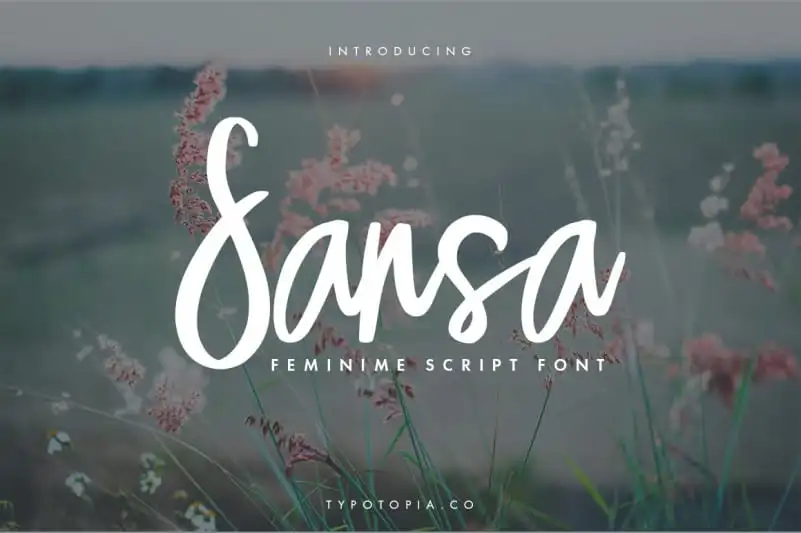
A Sansa Script Font é uma maneira criativa de adicionar personalidade a qualquer projeto que você esteja trabalhando. Ela não é apenas uma nova fonte para escrever letras, mas um instrumento visual único que pode transformar seu design no mais interessante possível. Foi projetada pelo Designer typotopia e é parte da categoria de Fonts Handwritten. Queda dos traços suaves do pincel criam uma aparência original, apropriada tanto para uso personalizado quanto para qualquer projeto. Cada sílaba tem sua própria identidade, promovendo um contato dinâmico e agradável entre os diferentes elementos gráficos usados. A Sansa Script Font é perfeita para qualquer momento ou projeto, seja de design web, impressão ou criação digital. Seu estilo único confere ao seu trabalho uma característica única, tornando-o imensamente versátil.